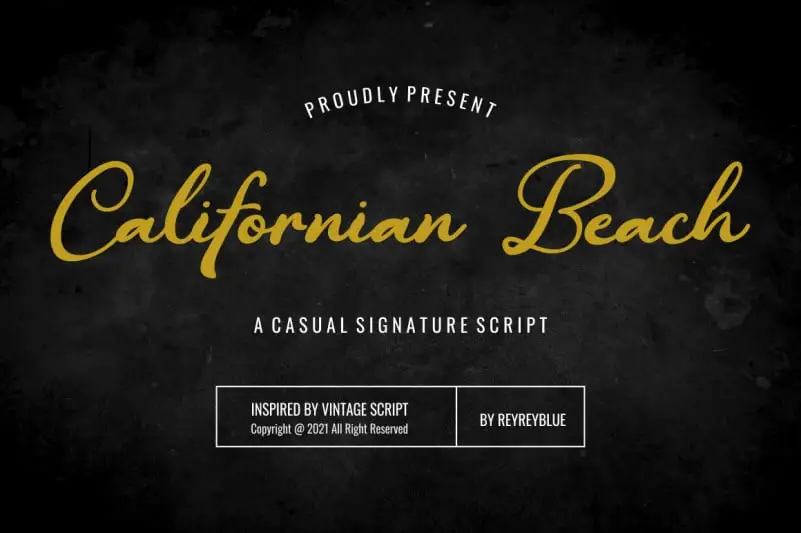
Californian Beach Script Font – Fonte Grátis
Californian Beach Script Font
A Californian Beach Script Font é uma escolha perfeita para quem busca estilos criativos no seu design editorial. Com sua escrita quase autêntica e seu fluxo natural e elegante, essa fonte leva um toque vintage ao seu projeto. Suas características naturais e suaves a tornam ideal para criar rótulos de produtos com uma aparência inovadora ou para adicionar um toque pessoal a sua identidade visual. Suas escritas quase autênticas são perfeitas para as etiquetas de produto que buscam personalidade ou os cartões de aniversário com citações criadas à mão. Além disso, essa fonte também destaca-se em editoriais e projetos de logomarca, tornando-a uma opção versátil que se adequa a um vasto número de aplicações, desde design editorial até publicidade digital. A designer ReyreyBlue traz para nós esta fonte com sua elegância única, garantindo que seu projeto tenha o toque perfeito em cada detalhe.